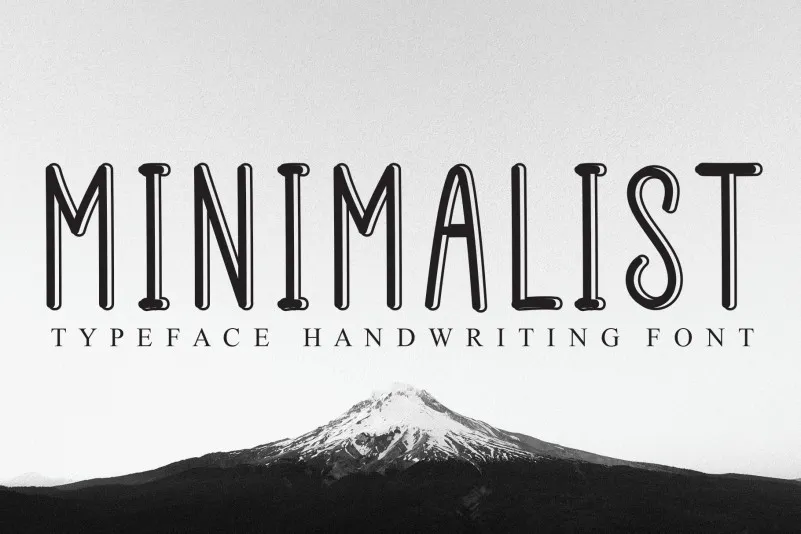
MINIMALIST Display Font – Download Grátis
MINIMALIST Display Font é uma fonte escrita à mão simples que exibe letras altas e delgadas. Ela transmite uma elegância suave e moderna, com um aspecto minimalista que se adapta perfeitamente a designs de criação criativas. Com sua tipografia caracterizada como escrita à mão, esta fonte é capaz de transformar ideias artísticas em algo mais vivo e impactante. Além disso, o Designer AndiKasStudio trouxe para este font único e singular uma qualidade que combina a simplicidade de um texto escrito à mão com uma linha estilizada e elegante. Como parte da categoria Handwritten Fonts, MINIMALIST Display Font oferece a oportunidade de incorporar elementos únicos que podem destacar qualquer projeto ou layout. E se você está procurando por uma fonte para dar vida ao seu próximo conceito criativo, não há melhor lugar do que explorar esta elegante opção minimalista.